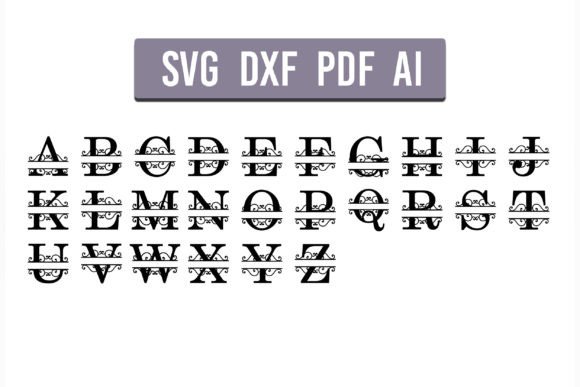
Split Letter Monograms Laser Cut Files
Encontrar los elementos de diseño adecuados puede ser un desafío, pero Split Letter Monograms Laser Cut Files ofrece una colección excepcional que eleva tu trabajo al instante.
Elaborado con precisión, Split Letter Monograms Laser Cut Files proporciona vectores limpios, tipografía suave y una licencia comercial para tu tranquilidad.